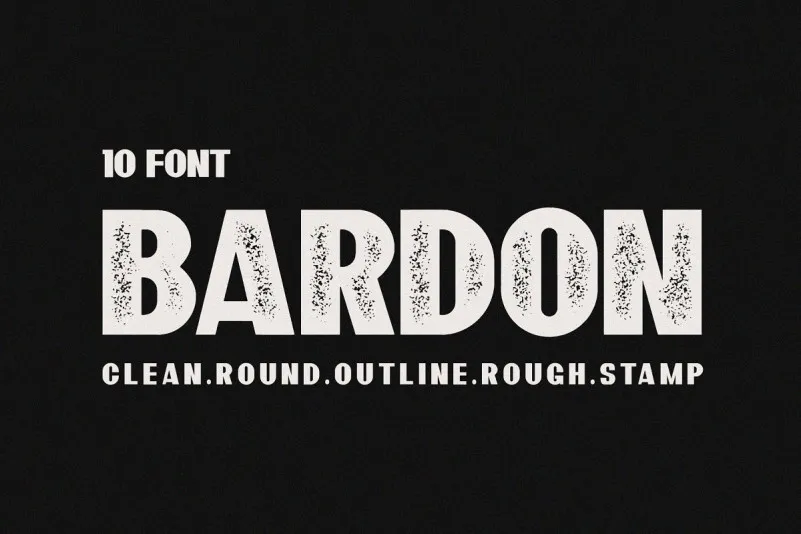
Bardon Font Family – Download Grátis
A Bardon Font Family é uma família de fontes góticas sans-serif que traz dez estilos únicos, criada pelo designer Sabr Creative. Esta fonte vintage gótica vem com alternativas estilísticas variadas e é perfeita para enriquecer headlines, identidade visual de marcas, editoriais, posters e muito mais. Seu design vintagem destina-se a tornar sua apresentação ou logomarca ainda mais impecável e chamativa. Este tipo de fonte é uma ótima escolha para aquelas pessoas que valorizam um estilo retro e sofisticado em suas criações digitais. A Bardon Font Family é uma seleção única de gráficos, perfeita para designers e criadores de conteúdo buscam algo que se destacará no mercado.